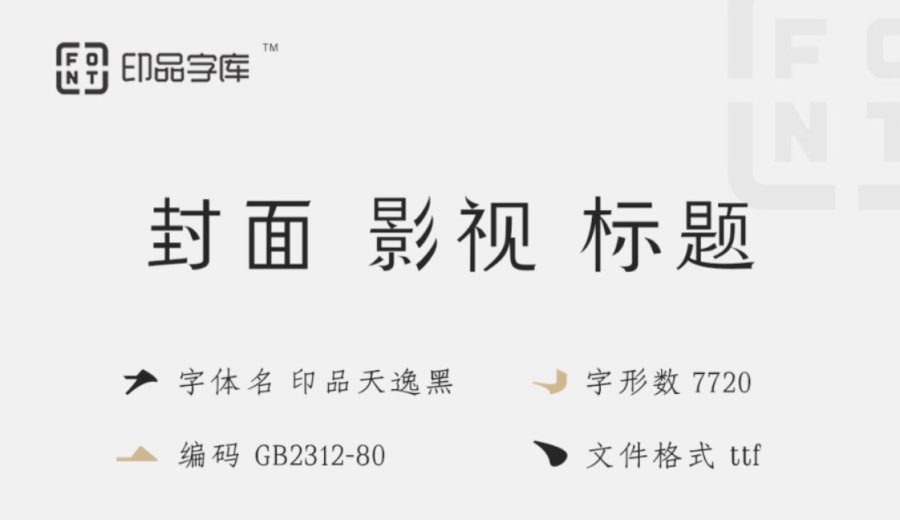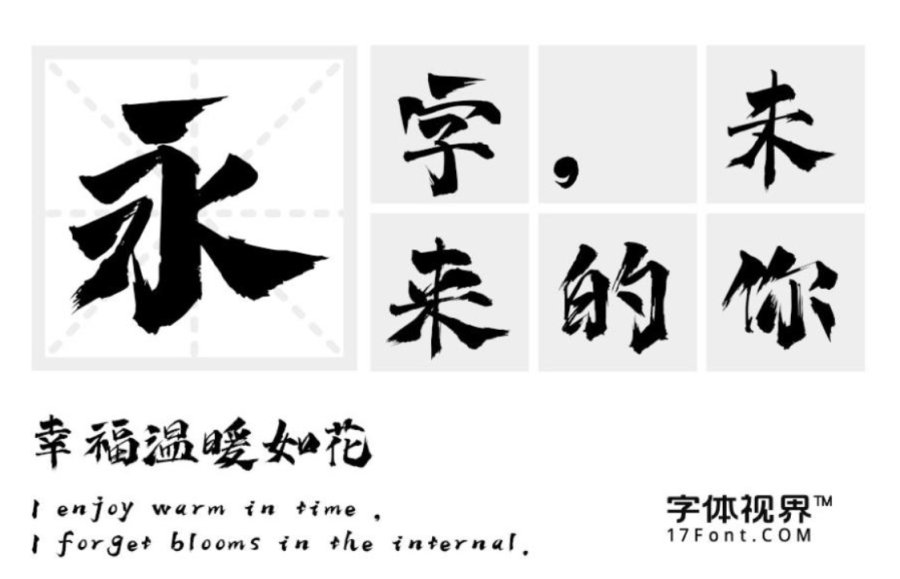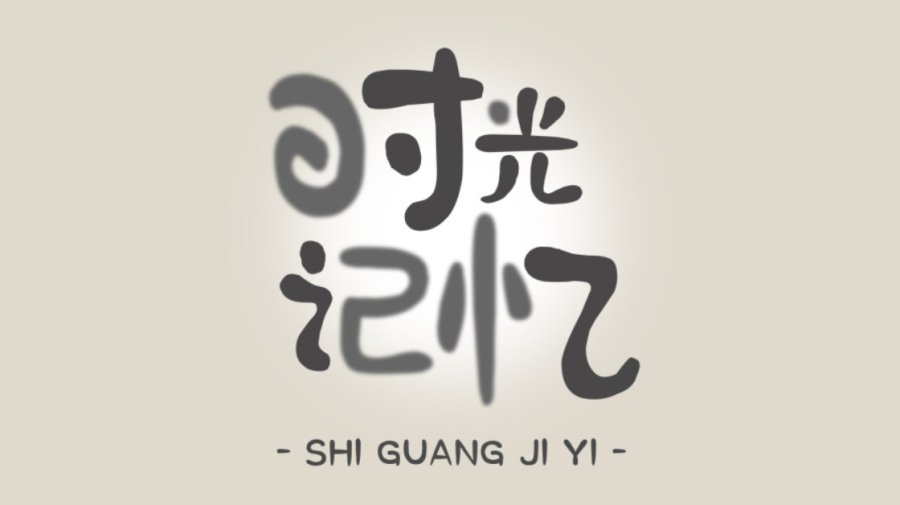
设计感十足的海报字体大全
海报设计的基本前提是要选择一款合适的字体,字体的选择要和整个作品的风格搭配的协调,字形体态的合理运用要和整体风格一致、与画面融合互补,与意境相互贯通,根据文字本身的情感和温度,展现出出图文说要传达的内涵。一般会选择的字体较于灵活多变,字形易认易读能轻易的看图片识别字体,具有记忆点。
印品天逸黑:这是一款海报设计运用上必不可少的黑体字,字体风格端庄简洁、个性鲜明不失时尚美感。稍有笔画修饰更富有现代感和简约风,规则冷静、适用性强应用面广。适合复古、怀旧、文化等主题的海报设计。
上首疾风书法体:这款字体风格锐利,钝点强力,夸张的笔锋增添了字体的活跃性,而且字体中粗细衔接,使字体显得生动。中国传统韵味非常强烈,用作于海报设计可以体现古朴的中国风和大气磅礴的庄重感。
印品百变马丁体:这款字体是印品字库携手今日动画IP百变马丁,共同打造的首款同名动画字体。字形比较圆润具有曲线型的风格特征。不会给人呆板的感觉,温馨轻松、自然可爱、活泼随心的感觉,适用于相对应感觉主题的海报设计。